Gratis dos volúmenes del 'Manuel Typographique', un clásico de la tipografía
Accede gratis a esta obra fundamental de la tipografía, escrita e impresa por Pierre-Simon Fournier en 1764
La historia de la tipografía abarca elementos apasionantes: avances técnicos, desarrollos artísticos e, incluso, revoluciones sociales que solo fueron posibles a partir del surgimiento de la imprenta. Dentro de ese contexto, algunos personajes y libros fueron claves y lo siguen siendo aún hoy.
El Manuel Typographique (Manual Tipográfico en español) del grabador y fundidor de tipos Pierre-Simon Fournier es uno de esos libros. Consiste en dos volúmenes y se considera una de las mayores fuentes de consulta para comprender los procesos de elaboración de tipografías en la era de la prensa. Además, contiene ejemplos de las ornamentaciones que Fournier utilizaba en su taller. Te contamos cómo acceder de manera gratuita a este material que forma parte de la Biblioteca Nacional de Francia.
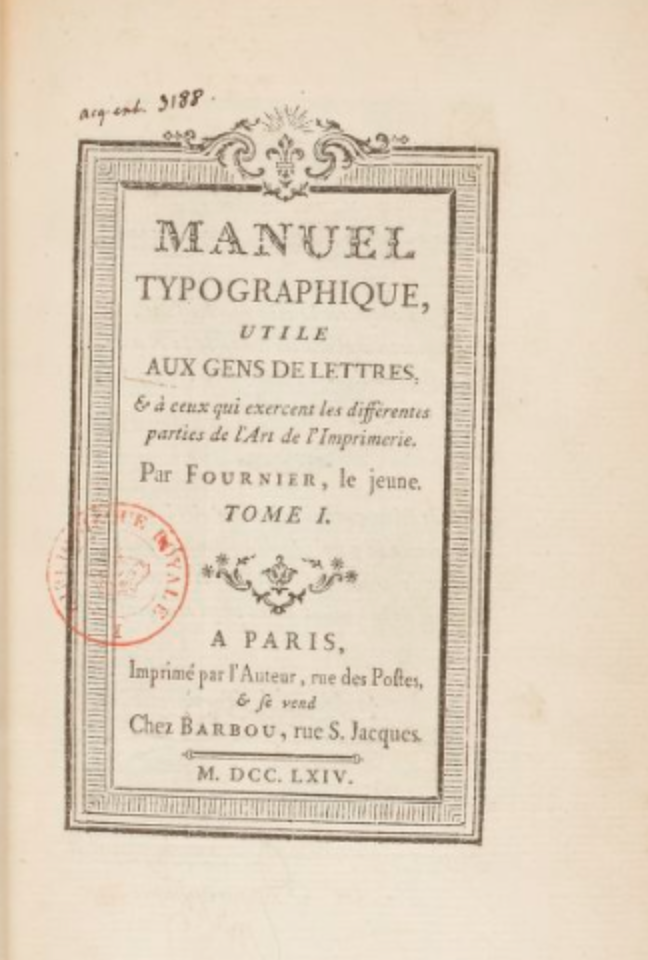
Fournier, un referente
Pierre-Simon Fournier nació en París en 1712. Su padre, Jean-Claude Fournier, venía de una familia de pintores reconocida por generaciones, lo cual orientaría su visión sobre la tipografía hacia un horizonte artístico.
Fournier aprendió dibujo en la academia St Luc de París y, a sus 17 años, comenzó a trabajar en la imprenta de su hermano, donde desarrolló el oficio. En ese espacio, Fournier comenzó a comprender íntimamente el funcionamiento de las tipografías.
En 1736 decidió crear su propia fundidora de tipos en la capital francesa. Su foco principal fue mejorar los procesos de impresión y crear nuevos caracteres que fueran eficientes tanto a la lectura como al uso de los recursos.
A él le debemos la creación de las letras itálicas, que aportaron modernidad y marcaron la estética tipográfica de una nueva era. El aporte de Fournier es interesante, también, en lo que se refiere a la ornamentación para las cuales creó métodos propios.
Seis años después de abrir su fundidora, en 1742, Fournier decidió compartir sus conocimientos y técnicas con el mundo. Comenzó publicando su célebre muestrario Modèle des Caractères de l'imprimirie (Modelo de caracteres de impresión en español) y Caractères de l'imprimirie (Caracteres de impresión). Más tarde, publicó el libro al que hacemos referencia, Manuel Typographique, uno de los clásicos de la tipografía.
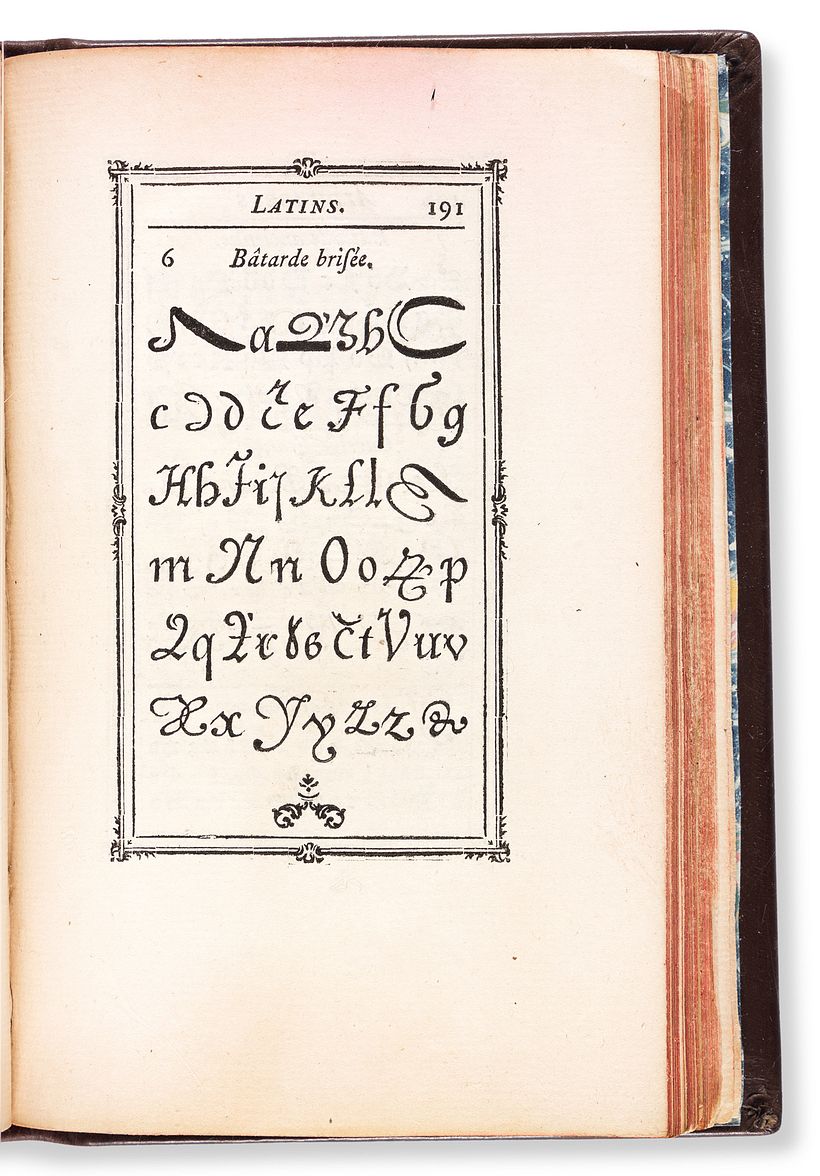
Sobre Manuel Typographique
Manuel Typographique cuenta con dos volúmenes publicados en 1764 y en 1766. Hoy se consideran obras maestras en cuanto a tipos, estilo y diseño. En ambas publicaciones se puede apreciar su estilo personal, sumamente innovador para la época y fundante de lo que vendría.
Su estilo presenta un gran contraste entre los grosores de los palos y revela una excelente economía de texto. En estos ejemplares también demuestra por qué su cursiva tenía reputación de ser la más legible de todas las cursivas de la época.
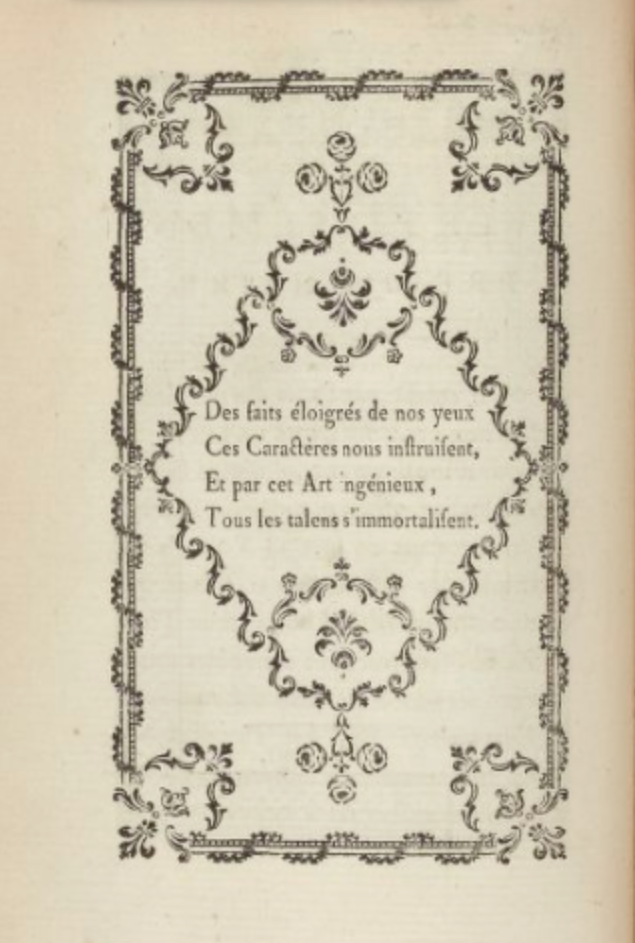
El principal aporte de Fournier
Más allá de su talento personal, la gran contribución de Fournier tuvo que ver con su determinación para unificar las medidas arbitrarias con las que, por entonces, cada fundidor fabricaba los caracteres. La solución que encontró en 1737 serviría aún dos siglos y medios después.
Entre sus ocurrencias, dio nombres de minerales preciosos a algunas medidas de referencias. Por ejemplo, llamó 'diamante' a la medida de 4.5 puntos y 'perla' a la medida de 5. Posiblemente, uno de sus mayores aportes a la posteridad fue un sistema completo de diseño con medidas estandarizadas cuyas partes se integraban perfectamente.